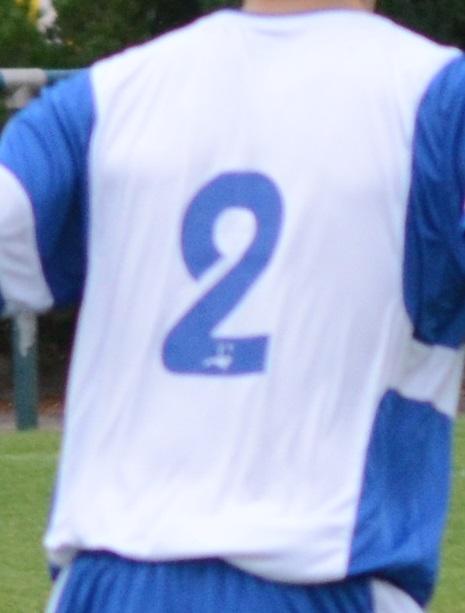
Fußball Schrift (Trikotbedruckung)
Habe WhatTheFont und What Fint is schon bemüht und nichtmal die Schriftart, ohne die Fallrückzieher-Männchen gefunden.
Hat jemand eine Idee?
Sie sind auf Trikots der Marke Uhlsport gedruckt, also vielleicht eine spezielle Schriftart dieser Firma?
Kenne mich da nicht so aus.
Dies kann man eigentlich nur bejaen. Trikotschriften sind zumeist speziell für die Sportartikel-Hersteller entworfen, weden von denen in der Regel über 2 Jahre verwendet und sind nicht selten auch markenrechtlich geschützt. Hatten wir hier ja schon mehrfach.
Die Fallrückzieher-Männchen sind kein Bestandteil der Schrift, sondern individuell eingesetzt – ganz im Stil der großen Vereine, die oft ihr Vereinslogo in jeder Zahl platzieren. Wohl auch um Plagiate besser verfolgen zu können.